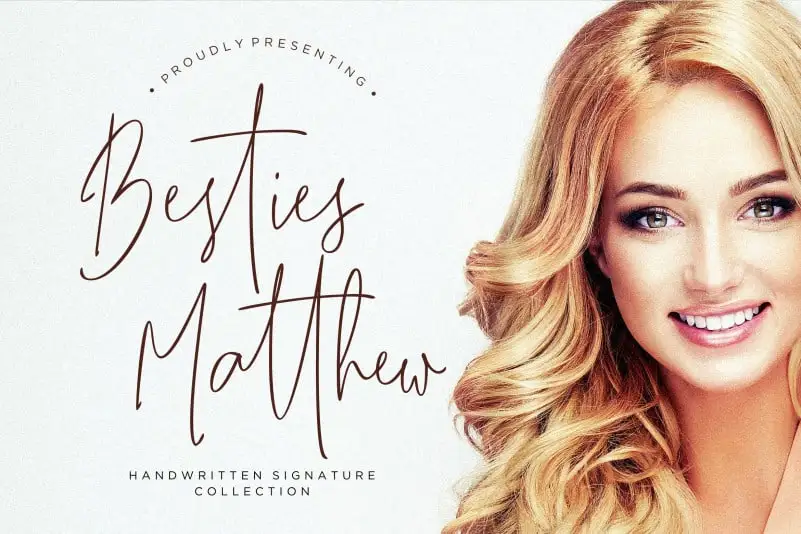
Besties Matthew Handwritten Font – Download Grátis
Aqui está uma versão curta e envolvente dos dois parágrafos para a descrição do download da font ‘Besties Matthew Handwritten Font’: Encontrei nesta fonte um estilo suave e descomplicado que pode dar vida ao seu próximo projeto criativo. A fonte “Besties Matthew Handwritten” é perfeita tanto para Instagram posts quanto para projetos DIY com gráficos feitos à mão, oferecendo um toque de luxo e elegância em qualquer ideia artística. Criada pelo Designer 178-MC, esta fonte é resultado da fusão entre uma tipografia sofisticada de estilo autêntico com o charme natural das escritas a mão. A font foi projetada para imitar uma escrita real, incluindo mais de 100 ligaturas que reforçam esse aspecto único. Se você busca um design contemporâneo e elegante, sem deixar de lado o toque pessoal dos desenhos a mão, então este é o seu font. A font ‘Besties Matthew Handwritten Font’ do Designer 178-MC está aqui para fazer suas criações ganharem vida!